Namen eintippen, Farbe wählen, PNG laden. Das ist alles, und es dauert etwa zehn Sekunden.
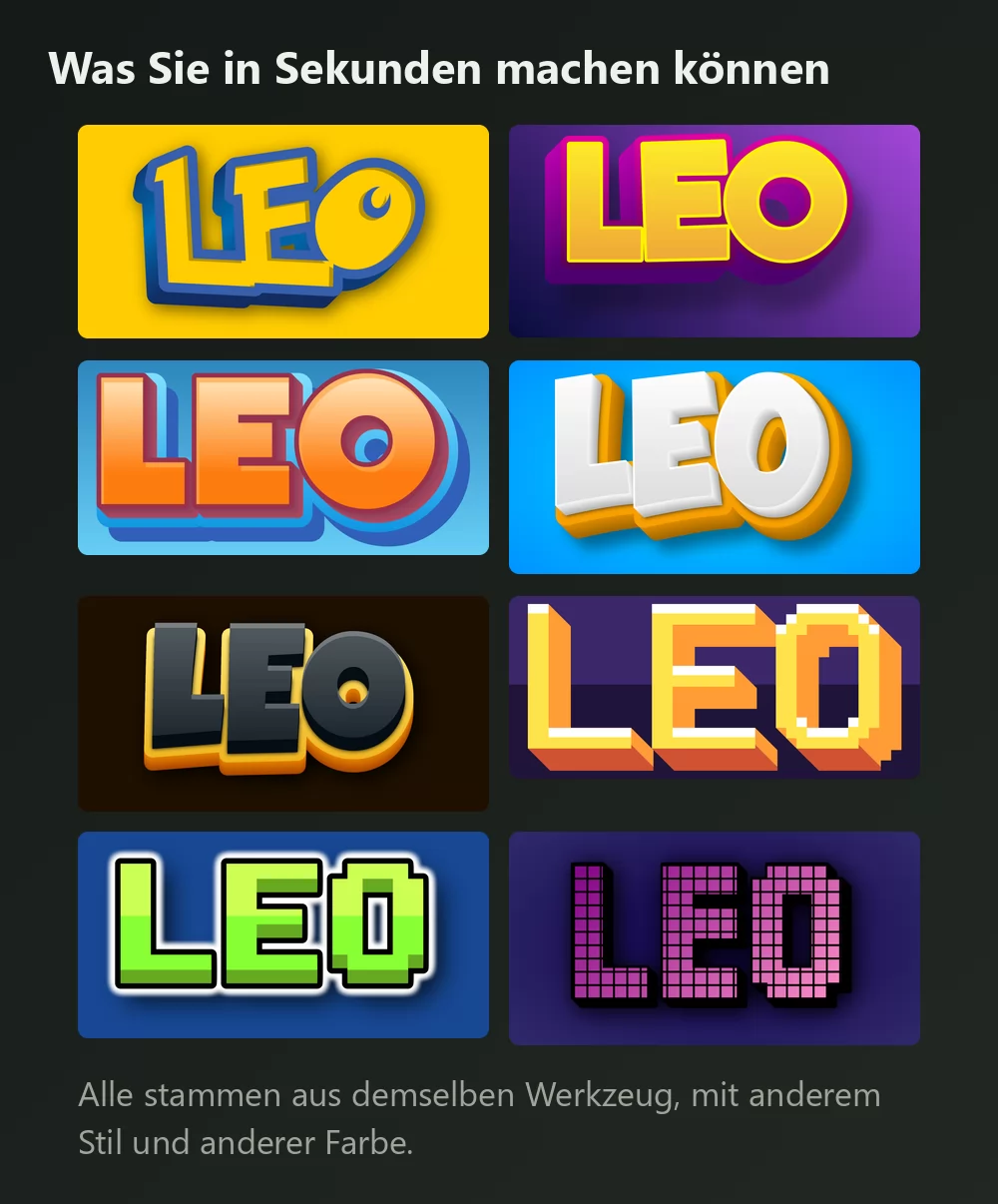
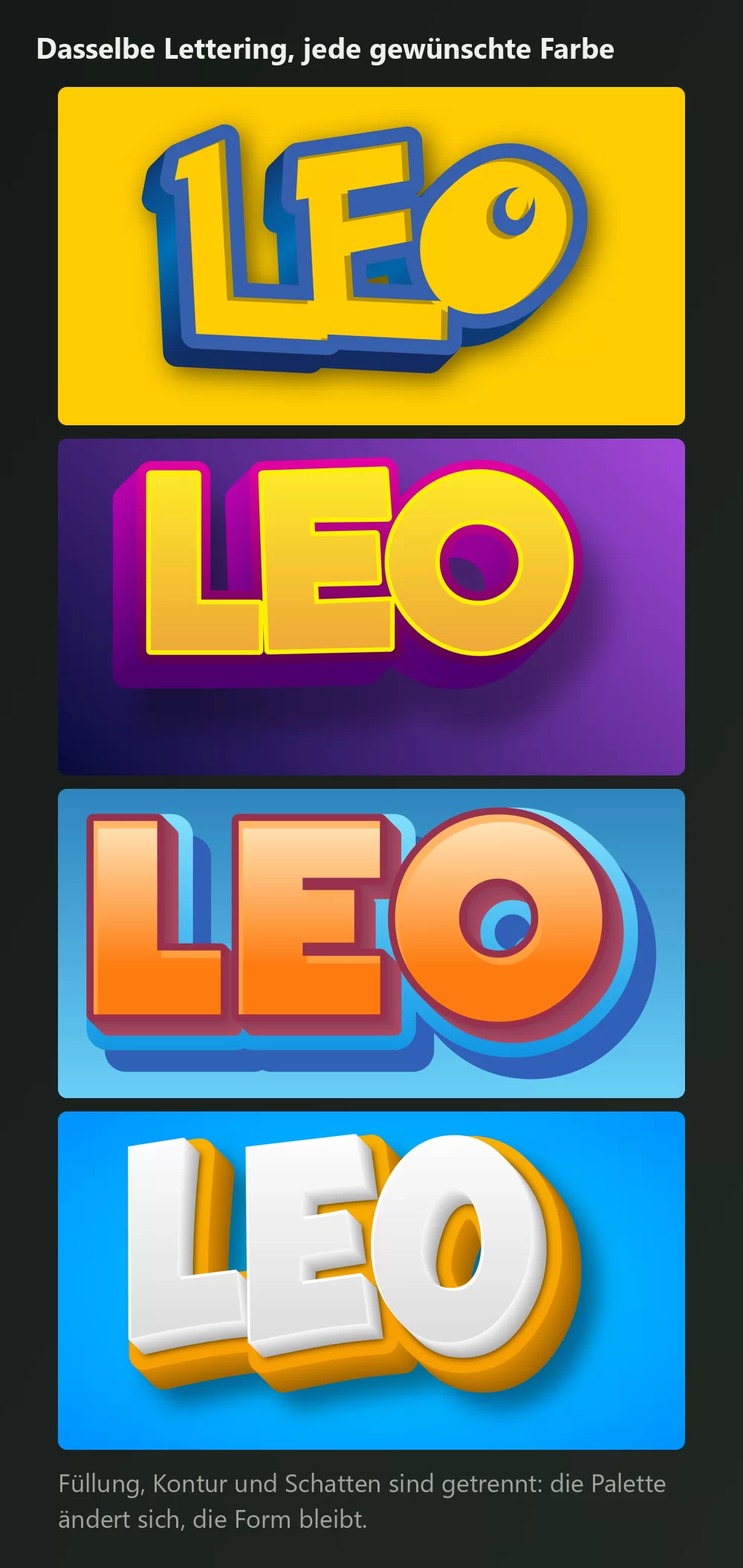
Der Styles-Tab hat drei Bereiche, und sie tun Verschiedenes:
- 3D und Füllung für die Farbe der Buchstaben selbst: einfarbig, Verlauf oder Muster.
- Konturen für den Rand, mit zwei Arten 3D-Kontur. Diese tiefblaue Kante ist es, die gelbe Buchstaben nach Pokemon aussehen lässt statt nach einem schlicht gelben Wort.
- Schatten für Schlag-, Außen- und Innenschatten, mit Weichzeichnung und Deckkraft.
Gelb mit blauer Kontur ist die Palette der Serie, aber die Form funktioniert in jeder Kombination.
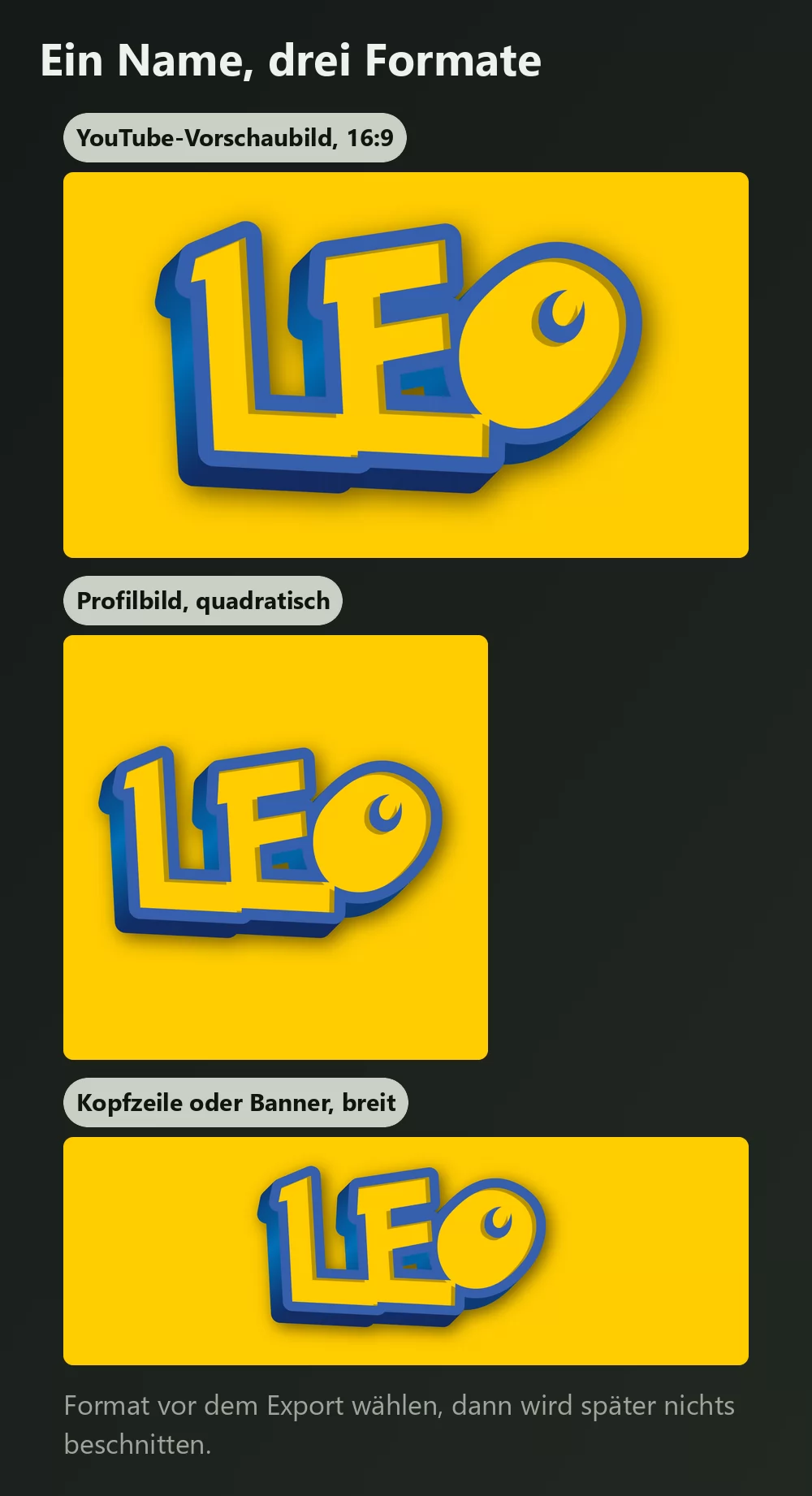
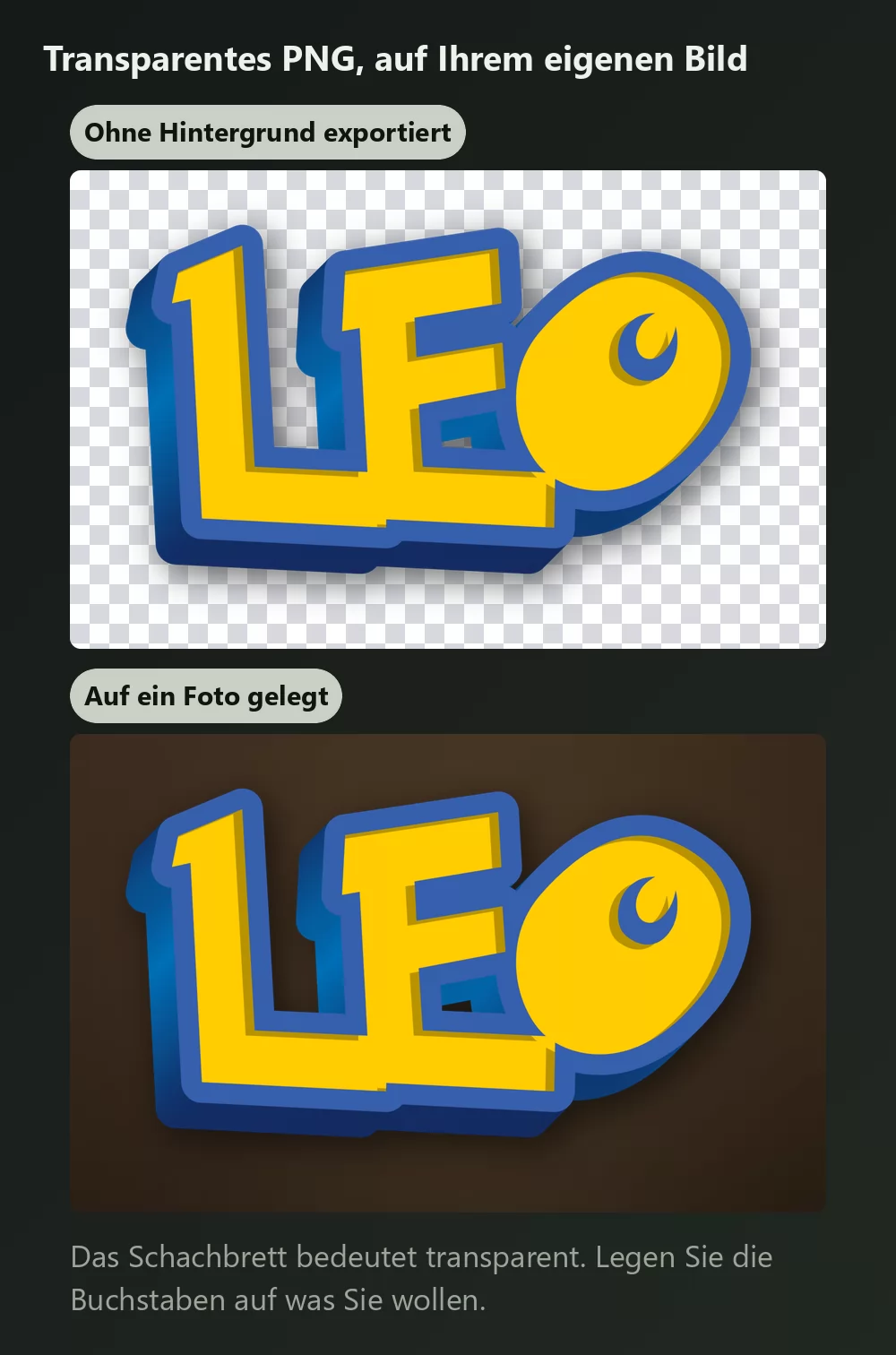
Lange Namen füllen die Breite schnell
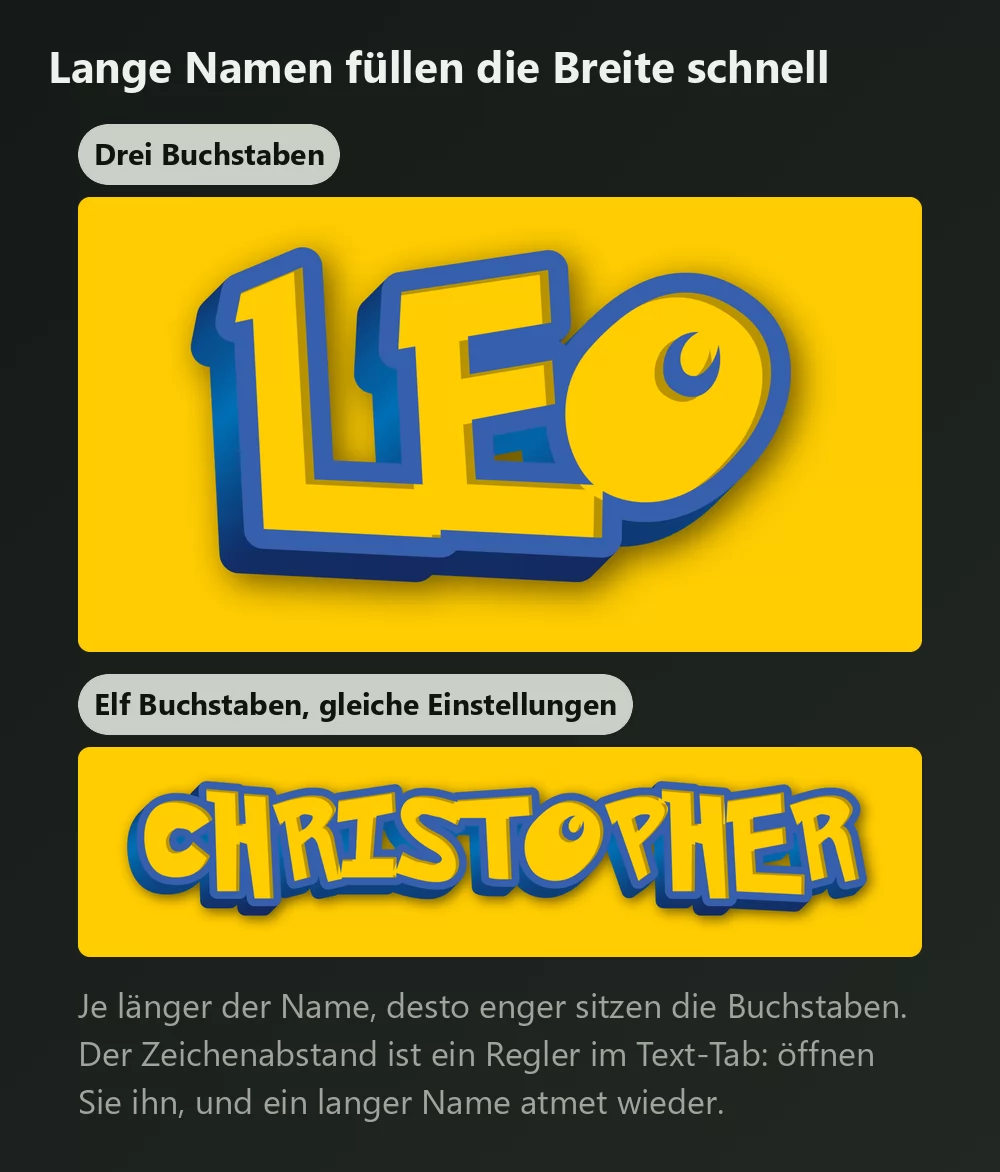
Je mehr Buchstaben, desto enger sitzen sie. Der Zeichenabstand ist ein Regler im Text-Tab: öffnen Sie ihn ein wenig, und ein langer Name wirkt nicht mehr gequetscht. Im selben Tab liegen Zoom, Zeilenhöhe, Krümmung und Drehung.
Den Text krümmen
Der Krümmungsregler gibt einem Titel seinen Schwung, und er ist der Unterschied zwischen einem flachen Wort und etwas, das gestaltet aussieht. Wenig reicht: ab einem gewissen Punkt fächern die Buchstaben auf und der Name wird schwer lesbar.
Logo-Look oder Spiele-Look?
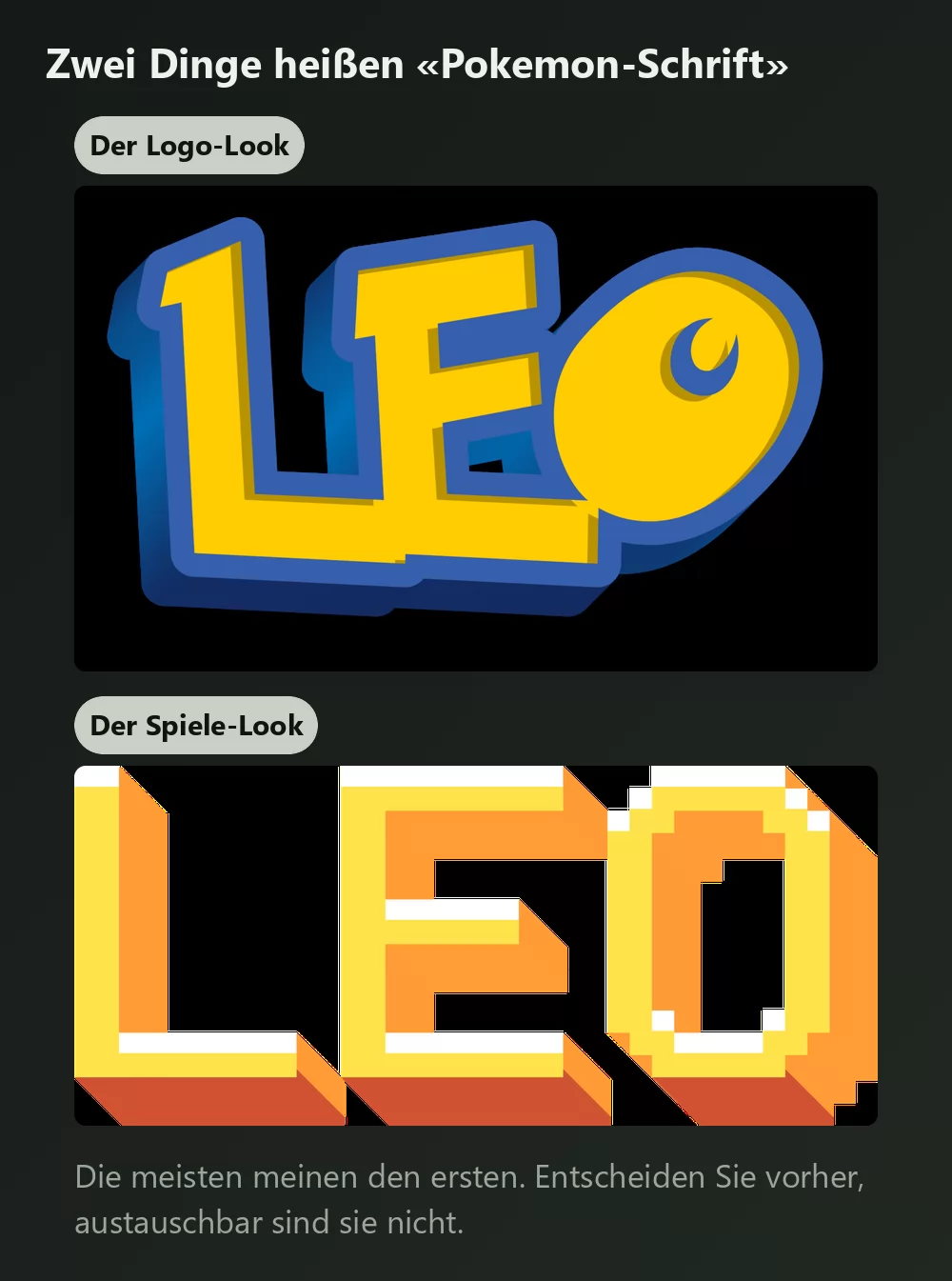
Zwei verschiedene Dinge heißen «die Pokemon-Schrift». Die meisten meinen das erste.
Der Logo-Look sind die dicken, runden Buchstaben mit kräftiger Kontur und etwas Tiefe, und genau das liefert der Generator oben.
Der Spiele-Look ist die kleine eckige Pixelschrift der Handhelds. Wenn Sie die wollen, bringt Sie ein 8-Bit-Pixel-Texteffekt dorthin.
Die Schrift heißt Pokemon Solid
- Pokemon Solid ist die gefüllte Fassung, die für einen Titel.
- Pokemon Hollow ist nur die Kontur, für große Größen, die Sie selbst füllen.
Eines sollten Sie erwarten: Die Schrift liefert Buchstabenformen und sonst nichts. Blaue Kontur, Füllung, Tiefe und Schatten sind Effekte, die Sie danach aufbauen, also genau die Arbeit, die der Generator für Sie erledigt.
Weitere Pokemon-Schriften, die man kennen sollte
- Pokemon GB bildet die kleine Bitmapschrift der Game-Boy-Spiele nach. Richtig für eine gefälschte Dialogbox, falsch für einen Titel.
- Pocket Monk ist eine andere Lesart des Logo-Letterings, nützlich, wenn Pokemon Solid nicht sitzt.
- Pokemon Pixel Font ist eckig mit gestuften Diagonalen, näher an einem Spielhallenbildschirm als an der Serie.
Alle sind Fan-Nachbildungen. Das offizielle Lettering wurde für die Marke gezeichnet und nie als Schrift veröffentlicht.
Pokemon-Text in Canva machen
Canva hat keine Pokemon-Schrift in seiner Bibliothek, und im Gratisplan lässt sich keine installieren. Der Weg drumherum: das Lettering als transparentes PNG bauen und hochladen. Es fügt sich direkt in ein Canva-Design ein und bleibt scharf.
Pokemon-Text in Photoshop machen
Pokemon Solid installieren, Text tippen, dann die Behandlung mit Ebenenstilen nachbauen:
- Kontur, auf Außen gesetzt, in einem tiefen Blau, ziemlich dick.
- Verlaufsüberlagerung oder eine gelbe Vollfarbe für die Buchstaben.
- Schlagschatten, nach unten und leicht nach rechts versetzt, niedrige Deckkraft.
Damit kommen Sie nah heran. Die Tiefe im echten Logo entsteht aus einer duplizierten, dahinter versetzten Ebene, die über alle Buchstaben hinweg gleichmäßig zu halten mühsam ist.
Pokemon-Text in Word machen
Schrift installieren, Text tippen, dann über Texteffekte Kontur und Schatten setzen. Words Effekte sind viel gröber als die eines Bildbearbeitungsprogramms: für alles, was gedruckt oder veröffentlicht wird, sieht ein exportiertes PNG besser aus als das, was Word bauen kann.
Auf dem Telefon
Sie können auf iOS und Android in den meisten Apps keine Schrift installieren und nutzen. Der Generator läuft im Browser des Telefons, der praktische Weg ist also: das PNG auf dem Telefon bauen, in die Galerie speichern und in der App einfügen, die Sie ohnehin benutzt haben.
Wie bekomme ich einen transparenten Hintergrund? Im Download-Tab das transparente PNG wählen und die Buchstaben dann über Ihr eigenes Bild legen.
Warum sieht mein Text auch mit der richtigen Schrift nicht wie das Logo aus? Weil eine Schrift nur die Buchstabenformen liefert. Blaue Kontur, Tiefe und Schatten sind Effekte darüber.